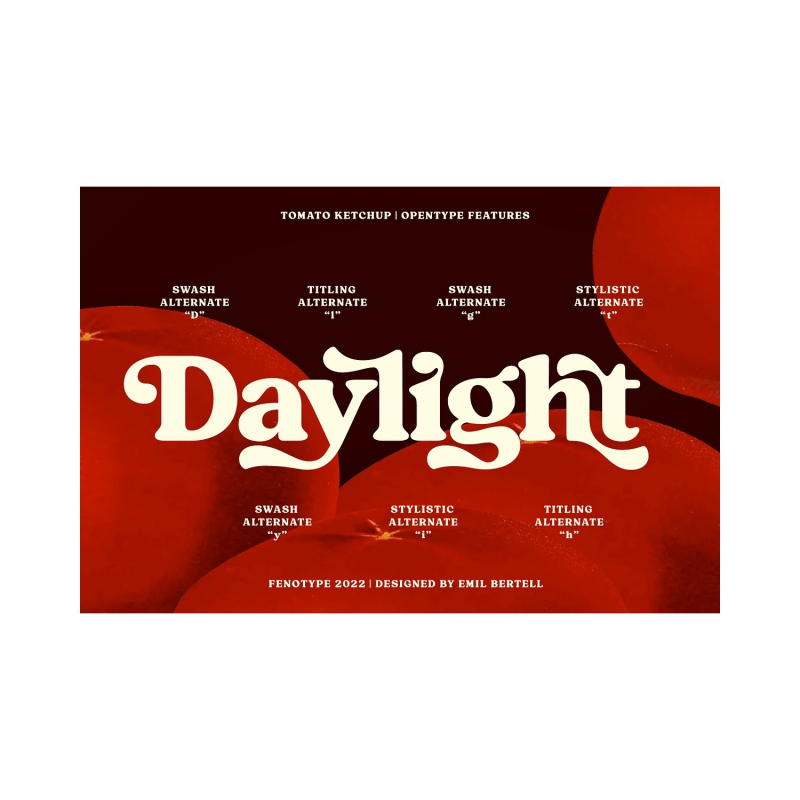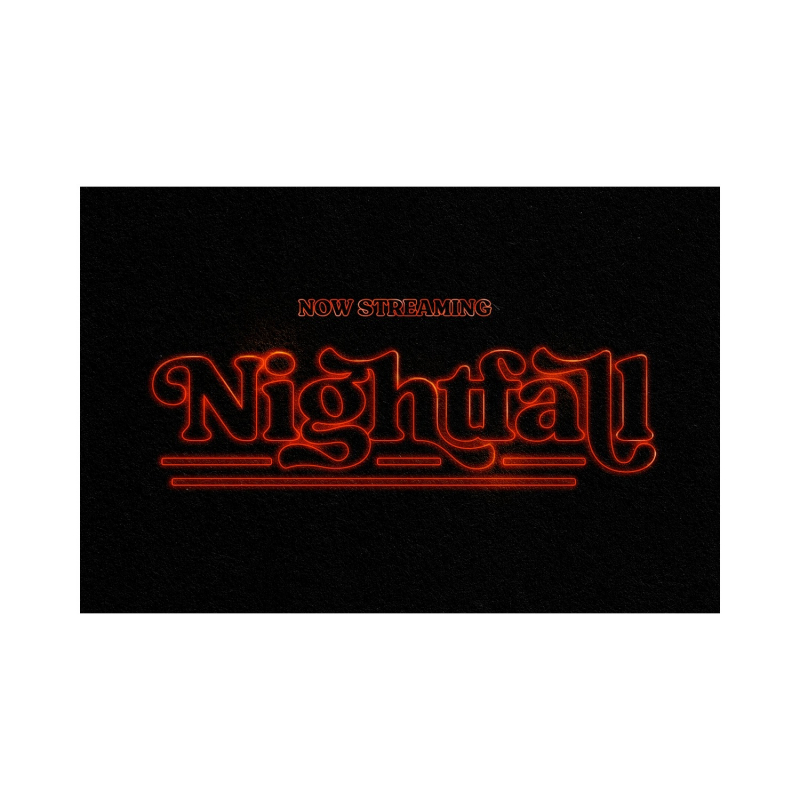
كاتشب الطماطم هو خط رقيق جريء على الطراز العتيق مع سحر غير مبال وثقة قوية. كاتشب الطماطم له نكهة مميزة وذكريات الشعور الدافئ المألوف. تم تجهيز كاتشب الطماطم ببدائل سياقية ، وسواش ، وأسلوبية ، وتمليك بالإضافة إلى حروف مركبة تقديرية والمزيد من البدائل الإضافية. يمكن الوصول إلى كل هذه الميزات بواسطة عناصر تحكم OpenType أو مباشرة من نافذة الأحرف أو الحروف الرسومية. الخط مشفر بشفرة PUA بحيث يمكنك استخدام الحروف الرسومية الإضافية في معظم برامج تصميم الرسومات. يتم تشغيل البدائل السياقية تلقائيا وتقوم ببساطة بإجراء تغييرات صغيرة لمنع تصادم بعض الأحرف. الميزات الأخرى اختيارية ويمكن استخدامها لحلول التصميم الأكثر جرأة.
كاتشب الطماطم هو محرف رائع للتصميم الجرافيكي المعاصر مع شعور معين بالألفة. إنه يعمل بشكل جيد على الشعارات أو التغليف أو رسومات المطاعم أو أي استخدام للعرض ، وكذلك في العناوين الرئيسية أو النصوص الأقصر. جرب كاتشب الطماطم مع تتبع منخفض للحصول على صور كلمات أكثر إحكاما ، أو إذا كنت ترغب في استخدامه بأحجام صغيرة حقا ، أضف بعض التتبع.